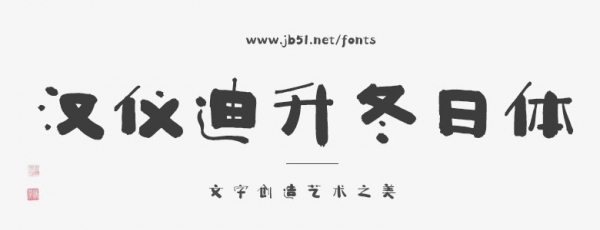
漢儀迪升冬日體 U,開啟入冬儀式感,慵懶過冬。字形蓬松,像厚厚的積雪也像軟軟的被窩,點畫隨性似雪花紛飛,粗厚溫暖的筆畫和纖細靈動的筆畫對比鮮明而平衡。這款字體是由漢儀字庫簽約作者迪升創(chuàng)作的「手寫四季」系列字體之一,適用于圖書繪本、影視綜藝、娛樂活動等多種應用場景,在寒冷的冬日里呈現(xiàn)一分柔軟的溫暖。